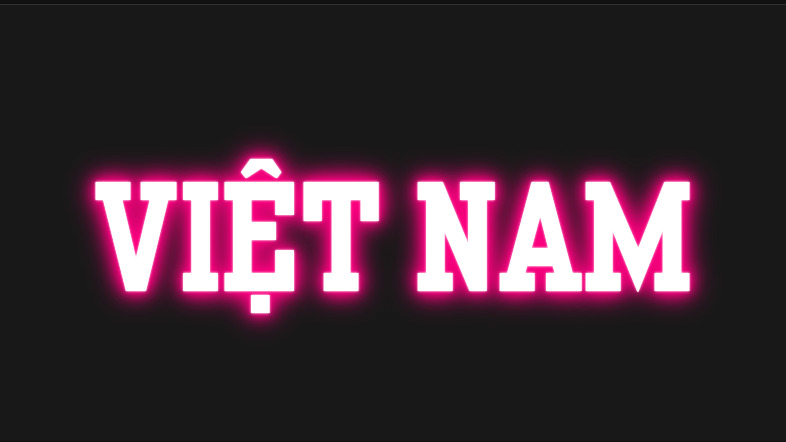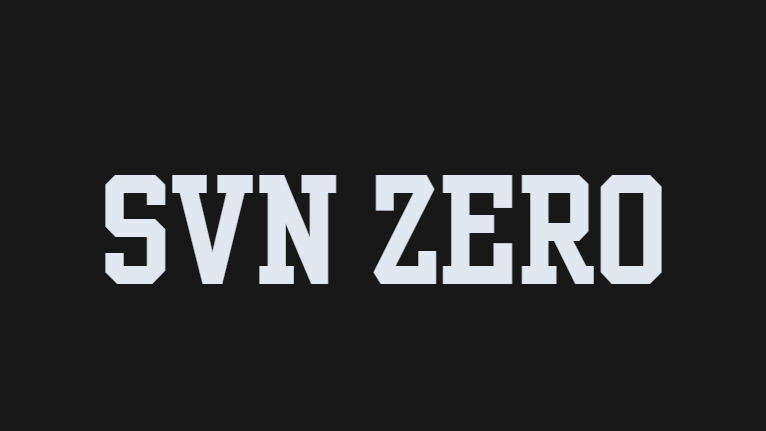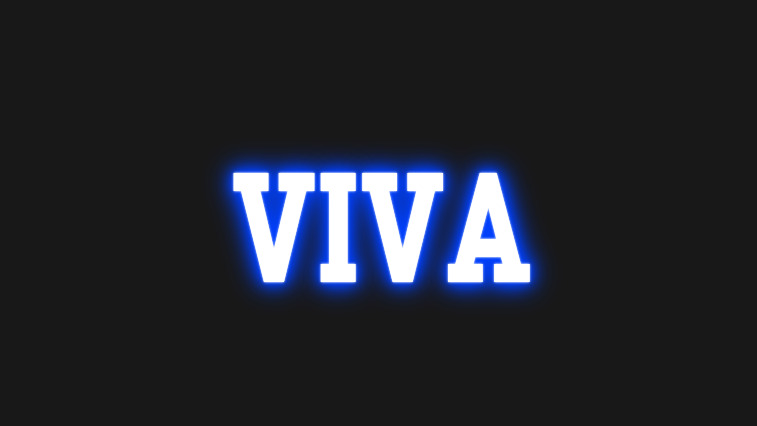
SVN Zero là bộ phông chữ không chân (Sans-serif) mang phong cách hình học tối giản và đậm chất tương lai (Futuristic/Techno), nổi bật với những đường cắt vát sắc sảo, cấu trúc mở rộng và diện mạo đậm chất công nghệ số. Được đội ngũ SVN tinh chỉnh hoàn thiện hệ thống dấu tiếng Việt, phông chữ này là lựa chọn số một cho các thiết kế logo startup công nghệ, bao bì thiết bị thông minh, phụ kiện gaming và ấn phẩm phong cách Cyberpunk hiện đại. Doozypack.vn cung cấp link download SVN Zero Font Việt hóa chuẩn kỹ thuật, giúp bạn sở hữu phông chữ đẳng cấp mà không lo gặp bất kỳ lỗi hiển thị dấu thanh nào khi thiết kế in ấn.
Đặc điểm thẩm mỹ độc đáo của bộ font SVN Zero
Zero không đi theo sự cầu kỳ rườm rà của các phông chữ truyền thống; nó mang đến một ngôn ngữ thị giác thuần khiết, kết hợp hoàn hảo giữa vẻ đẹp của hình học chuẩn xác và tính ứng dụng của kỷ nguyên số.
Phong cách Geometric Techno hiện đại và tối giản
Đặc trưng lớn nhất của SVN Zero là các đường nét thẳng tắp dứt khoát kết hợp cùng những đường cong bo tròn tinh tế. Cấu trúc chữ sở hữu độ dày nét đồng đều, các khoảng hở trong chữ (counter) được mở rộng tối đa, tạo nên một không gian thị giác vô cùng thông thoáng và minh bạch. Khi đặt Zero làm tiêu đề trên bao bì, thương hiệu của bạn sẽ ngay lập tức toát lên vẻ ngoài hiện đại, tân thời và khẳng định vị thế dẫn đầu về công nghệ.
Cấu trúc hình khối chuẩn xác mang tinh thần tương lai
Các ký tự của SVN Zero Font sở hữu tỷ lệ hình học cân bằng tuyệt đối, gợi nhớ đến những bảng điều khiển tàu vũ trụ hay các mã code lập trình tinh gọn. Phong cách tối giản này giúp các tiêu đề bản thiết kế giữ được sự đĩnh đạc, chuyên nghiệp và có chiều sâu thị giác ấn tượng, rất phù hợp với xu hướng đồ họa Minimalism đang thống trị thị trường quốc tế hiện nay.
Ưu điểm nổi bật của bản SVN Zero Font Việt hóa
Khi ứng dụng các phông chữ hình học công nghệ vào thị trường trong nước, sự chỉn chu về dấu câu là yếu tố quyết định đến tính chuyên nghiệp của bản thiết kế:
- Khắc phục triệt để lỗi dấu tiếng Việt: Phiên bản SVN Zero Font Việt hóa đã được đội ngũ thiết kế trau chuốt thủ công từng dấu câu. Các dấu sắc, huyền, hỏi, ngã, nặng được vẽ với tỷ lệ hình học chuẩn mực, không gây cảm giác chắp vá hay làm mất đi tính cân đối nguyên bản của thân chữ.
- Bảo đảm tính đồng nhất thương hiệu: Việc tải font Việt hóa SVN Zero chuẩn giúp bạn tự tin dàn trang tiêu đề tiếng Việt mà không lo hiện tượng lỗi ô vuông hay nhảy về font hệ thống khô khan.
03 Ứng dụng thực tế của font SVN Zero trong sản xuất bao bì tại Doozypack.vn
Sự hiện đại và tinh gọn của Zero mang lại hiệu ứng thị giác đắt giá trên các dòng sản phẩm bao bì thực tế do Doozypack.vn sản xuất:
- Hộp đựng phụ kiện Công nghệ & Gaming: Tiêu đề thương hiệu in bằng font Zero kết hợp kỹ thuật ép kim bạc lạnh trên giấy Ivory cán màng mờ tạo nên vẻ ngoài vô cùng cao cấp và đậm chất công nghệ cao.
- Bao bì mỹ phẩm tối giản & Dược mỹ phẩm: Nét chữ hình học sạch sẽ giúp vỏ hộp toát lên vẻ đẹp thuần khiết, an toàn và minh bạch về thành phần sản phẩm.
- Tem nhãn dán thiết bị thông minh: Cấu trúc chữ rõ ràng giúp các thông số kỹ thuật trên tem decal trở nên dễ tra cứu và chuyên nghiệp hơn trong mắt người tiêu dùng.